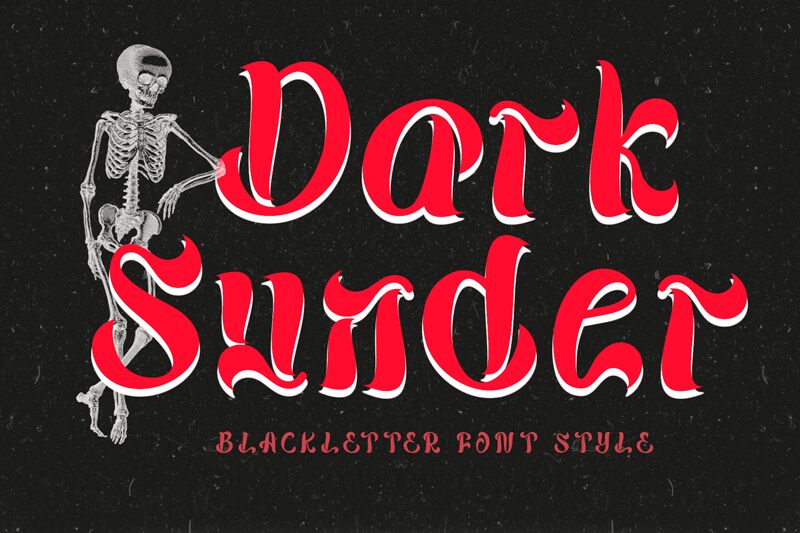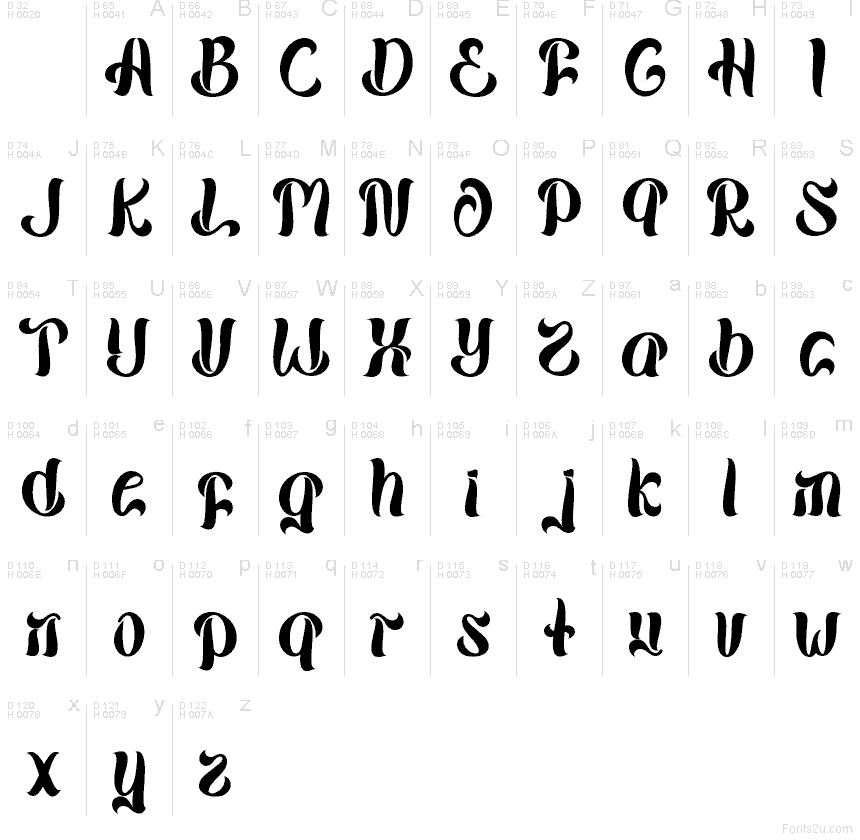
Dark Sunder
Dark Sunder de Yoga Letter es una tipografía gótica gratuita que destaca por sus curvas caligráficas, un contraste definido entre formas redondeadas y puntiagudas, y una mezcla dramática de arcos estrechos y trazos sinuosos. Aunque las letras evocan la tradición del blackletter clásico, las formas se han suavizado para lograr un ritmo más fluido que dota a la tipografía de una personalidad propia.
Esta fuente gratuita es perfecta para títulos de carteles, portadas de libros, invitaciones góticas, arte de álbumes y proyectos de branding que requieran un aire histórico y oscuro. Sus trazos fluidos y formas estilizadas también funcionan de maravilla en logotipos, folletos de eventos y marcas denominativas decorativas donde la letra misma es parte de la atmósfera visual.